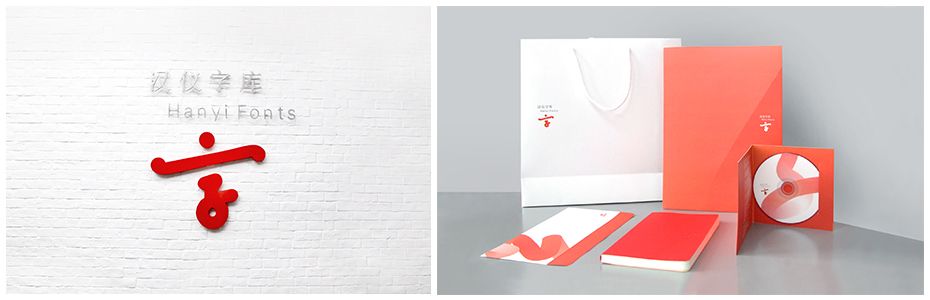
汉仪字库
关于“汉仪”
北京汉仪科印信息技术有限公司(以下简称"汉仪公司")成立于1993年,是中国大陆最早专业从事字形设计、字库产品开发、汉字信息技术研究、汉字应用解决方案的,拥有核心自主知识产权的文化创意与高新技术企业。
2011年以来,汉仪公司一直承担着被列入《国家"十一五"时期文化发展规划纲要》的重大建设项目,93年成立至今,汉仪已经向国内外市场推出300余款中文字库。
秉承着传统字库行业的工匠精神,汉仪字库复刻的清代扬州雕版印刷极盛时期标志的康熙版《全唐诗》雕版字体,与黑体大家齐立老师倾力设计的字库产品汉仪旗黑,以及同期创作的元隆黑、铁线黑、新人文宋、小麦体等大量优秀字库作品皆活跃于一线应用市场,受到行业内外的一致好评。
除了在字体创意、字体设计的专业研究外,汉仪公司更加注重市场、技术前沿的探索,面对飞速发展的移动互联网产业,汉仪实时关注字体在不同应用环境下的使用表现。
2013年,汉仪全资收购了上海驿创,凭借独创的fulltype小字库技术,真正的实现了从字体创意、设计到技术内嵌的全方位解决方案,开始了汉仪字库的互联网征程。凭借可以将字库大小做到300k的独家技术,在传统授权领域以及嵌入式领域成功合作了如大众汽车、网易新闻、高通、展讯、MTK等大型品牌客户,更在2013年开始,扩大了互联网2c领域的合作,成功牵手拥有8亿手机用户的腾讯手机QQ平台,并成功引入了明星字迹,创造了字库行业面向大众人群尤其年轻人群的全新商业模式。
汉仪将继续秉承着专业的字库公司的工匠精神,以专业的字库产品为中心,继续面向设计师人群的提供专业的字体服务;同时,汉仪将继续以互联网为载体,面向2c人群提供更加优秀的以文字为载体的移动互联网产品。汉仪正在成为一家以字库为核心产品,具备文化创意能力,互联网延伸能力的高科技公司。